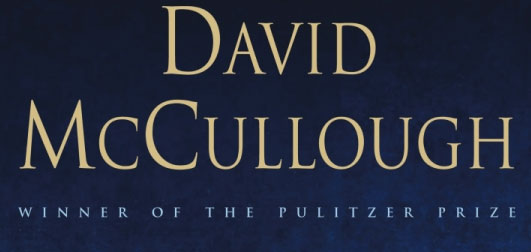
Trajan, die Killerschrift – ein FilmAm Rande der NewYorker TypeCon fand das Typophile Film Festival #
1 statt. Die Attraktion des Abends war der 10-minütiger Breitwandfilm
»Etched in Stone« von Cheshire Dave, ein typografischer Horrorfilm
über die Vormacht der Schrift Trajan bei der Filmplakatgestaltung. Der Film
...
![]() Unter den »besseren« US-Plakatgestaltern und Buchcover-Designern
ist die Adobe-Schrift Trajan das Hassobjekt Nummer 1. Wie eine Seuche hat sich
die römische Type verbreitet, seit Jahren dominiert sie den US-Titelsatz.
Ein Blick auf Platz 1 der New York Times Bestseller-Liste
bestätigt
das:
![]() Wir sehen Trajan, doch damit nicht genug: ![]() wir sehen sie mit unechten Kapitälchen, horizontal gestaucht (»David McCullough«) und fies gesperrt (»Winner ...«). Wer hierzulande einen US-Fake-Titel, zum Beispiel für einen Fernsehfilm, gestalten möchte, hat es in diesen Zeiten recht einfach, wie dieser 5-Minuten-Schnellschuss belegt: ![]() Trajan ist in den USA eine Titelsatz-Ikone. Dies als Vorgeplänkel für den wunderbaren, spannenden Film Etched in Stone, der jedoch 37,5 MB groß ist ... aber die Datenmenge ist gut investiert. Zur Konzentration und um in den Genuss des Bass-lastigen Soundtracks zu kommen, empfehle ich das Anschauen mit Ohrstöpsel. Viel Vergnügen. Herausgegeben: Do - August 4, 2005 at 02:39 nachm. | |